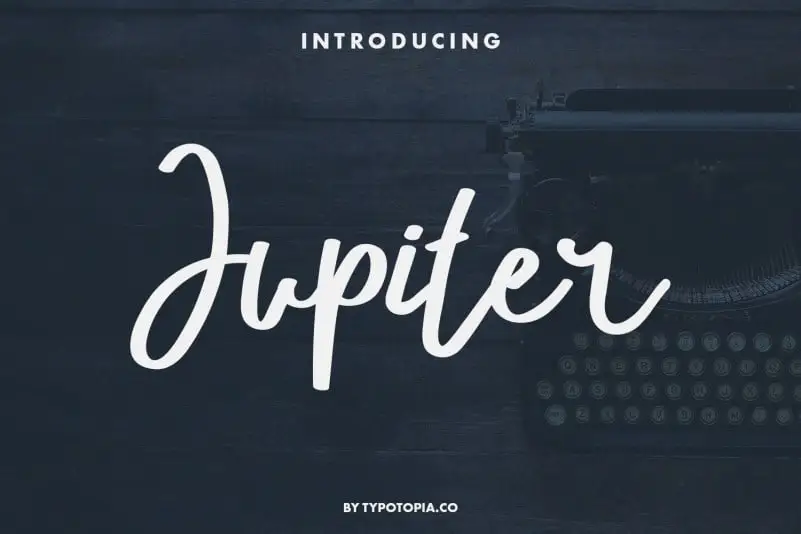
Jupiter Fancy Script Font – Download Grátis
A fonte ‘Jupiter Fancy Script Font’ é uma elegante seleção para aqueles que buscam personalidade e sofisticação em seu trabalho visual. Especialmente projetada para logos, cartazes, materiais de escritório, revistas, menus, livros, convites, cartões de visita, embalagens, etiquetas, roupas e marketing, esta fonte oferece uma abordagem criativa que encanta a todos os setores da comunicação visual. Desenvolvida pelo designer typotopia, é perfeita para aqueles que buscam um estilo único capaz de destacar sua marca entre a multidão. Com suas linhas fluidas e detalhes elaborados, esta fonte permite criar designs distintos e impecáveis, garantindo uma impressionante expressividade visual em qualquer projeto. Não importa se está criando um cartão de visita para empresas ou um cartaz para eventos, ‘Jupiter Fancy Script Font’ será o seu melhor aliado ao tornar seus projetos ainda mais atraentes e memoráveis.